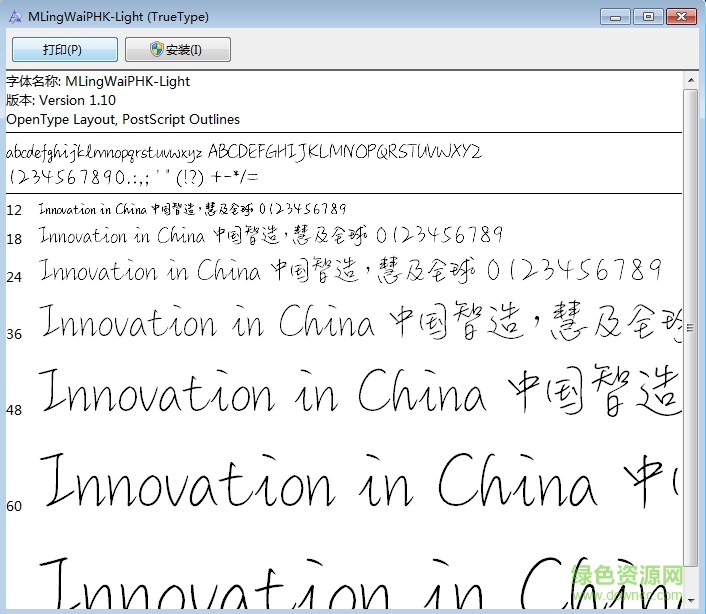
蒙納凌惠體是一款字跡連貫微草的蒙納字體,清秀的外觀(guān)讓你的文字書(shū)寫(xiě)更顯飄逸灑脫,適合情書(shū)、古詩(shī)詞等臨摹和謄寫(xiě),喜歡的朋友快來(lái)綠色資源網(wǎng)下載吧!
蒙納凌惠體用鋼筆寫(xiě)就,一筆一劃都透著書(shū)卷氣和灑脫感,適用于書(shū)面臨摹、文印排版、編輯打印等行業(yè)。